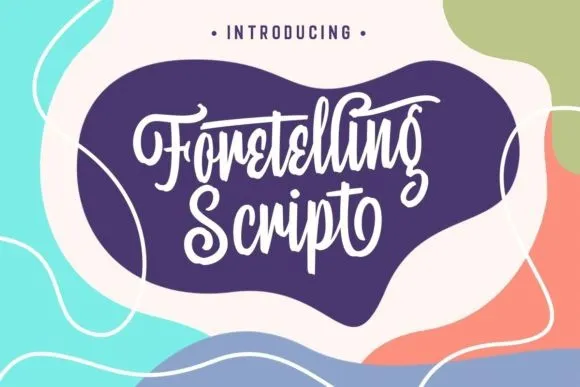
Essa é uma fonte círula forte e bold que foi criada por quem se chama letterhend. Ela é PUA (Propriedade Unicode Avançada) codificada, o que significa você pode acessar todos os gilis e swashes sem qualquer dificuldade! Com sua linha variável, linhas suaves, belos glyphos e alternativas de extrema beleza, ela mantém suas influências clássicas do cálamo ao mesmo tempo em que se mostra contemporânea e fresca. Que você caia no amor desta fonte e leve seus projetos ao nível mais alto! Essa é uma excelente opção para quem busca um texto elegante com a atualidade de hoje.